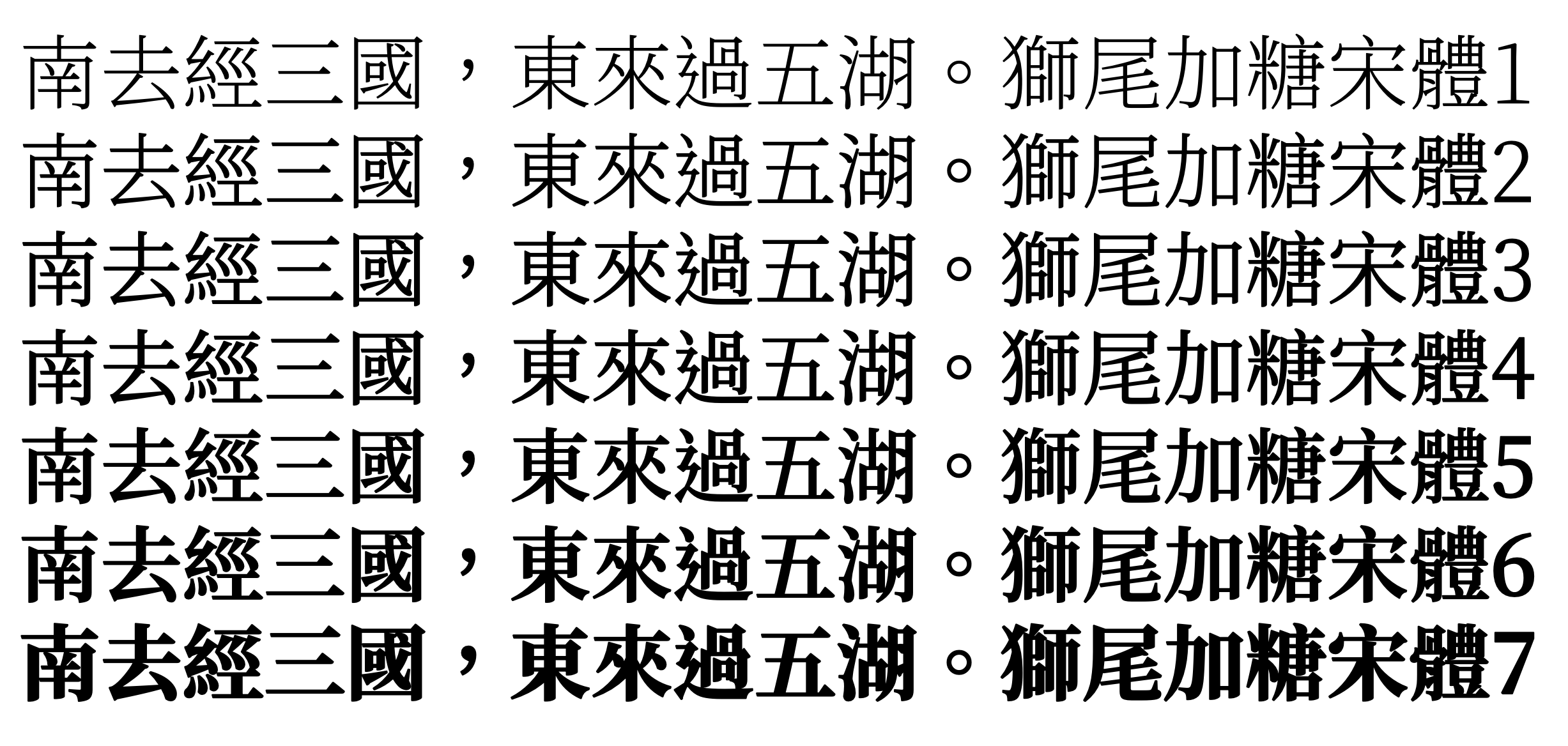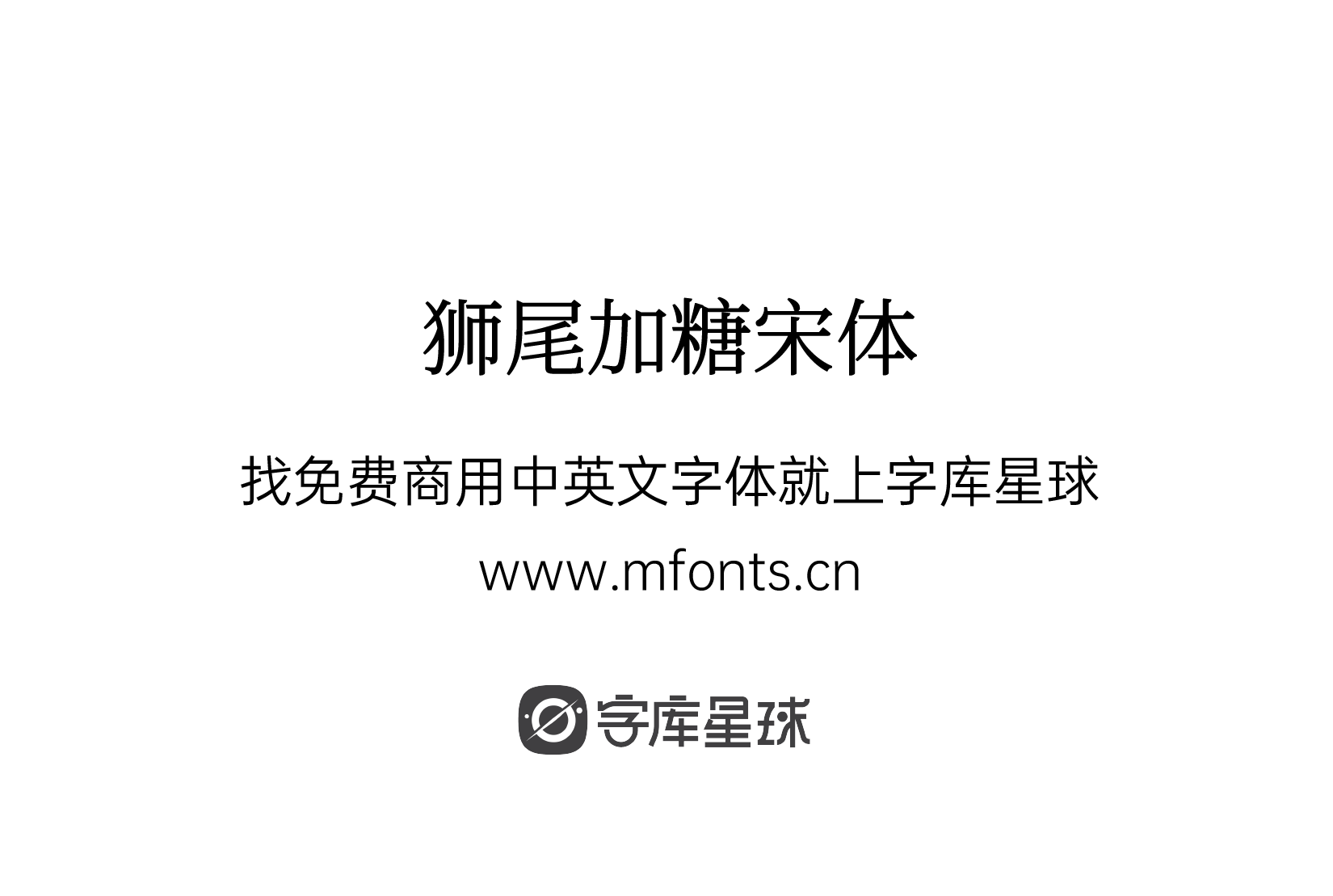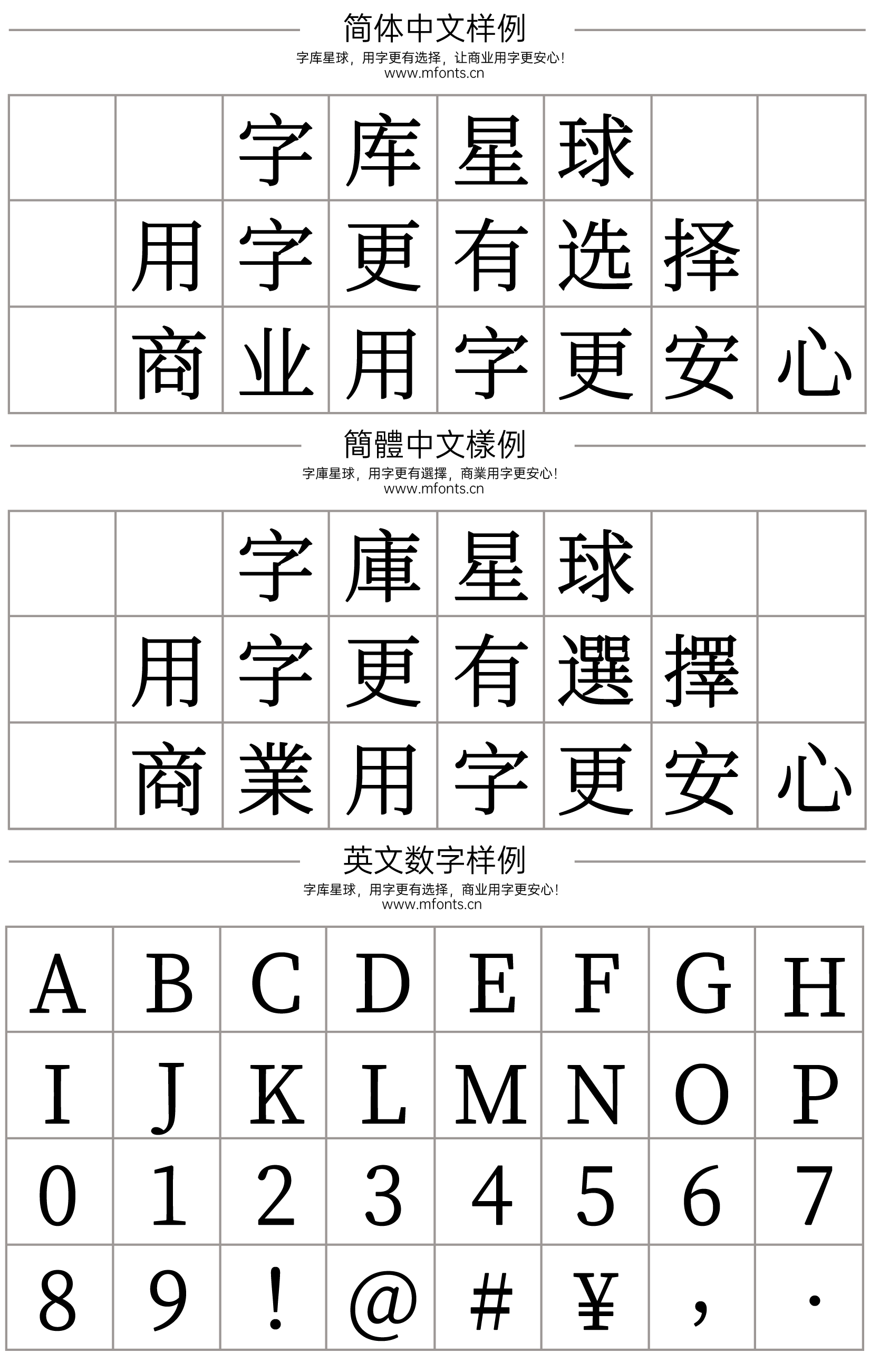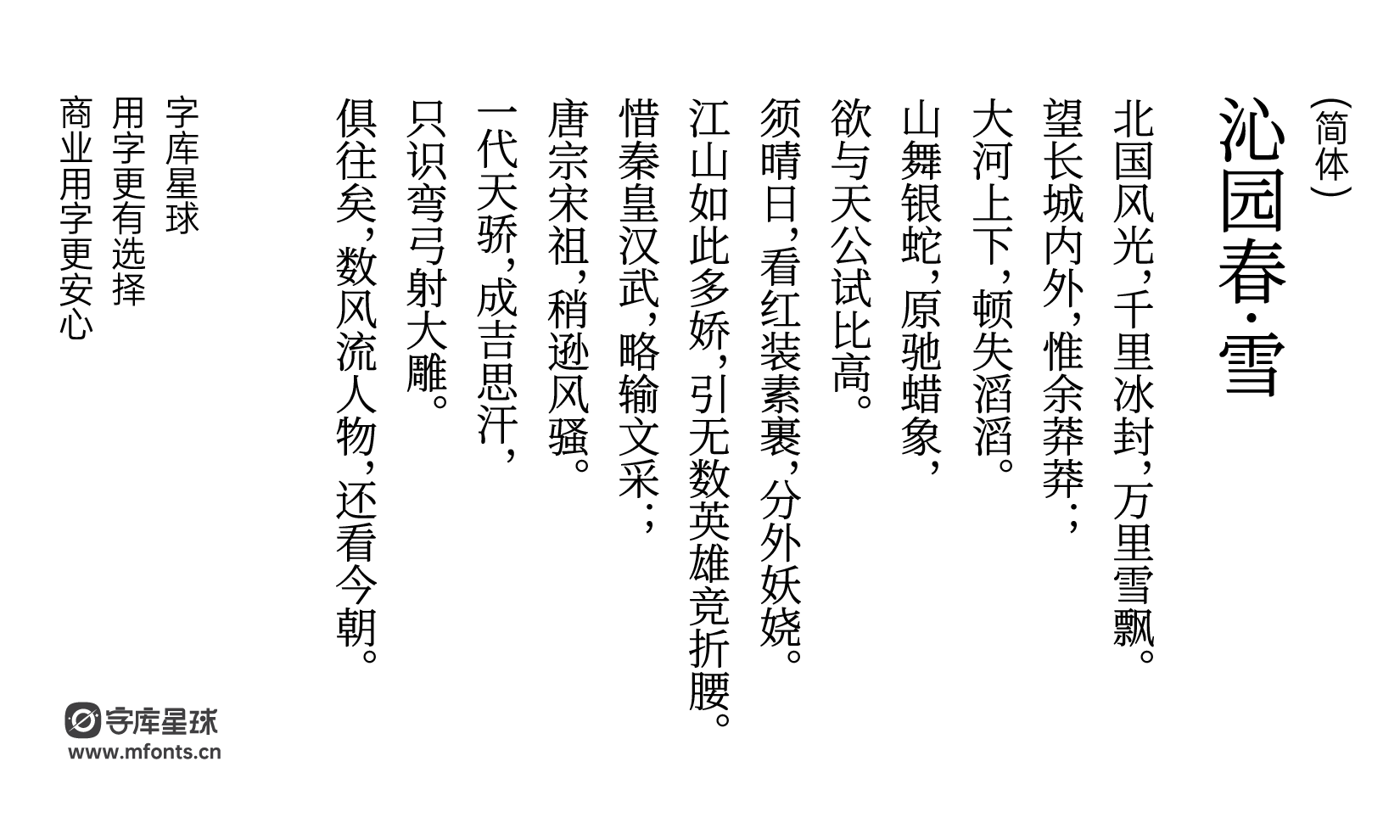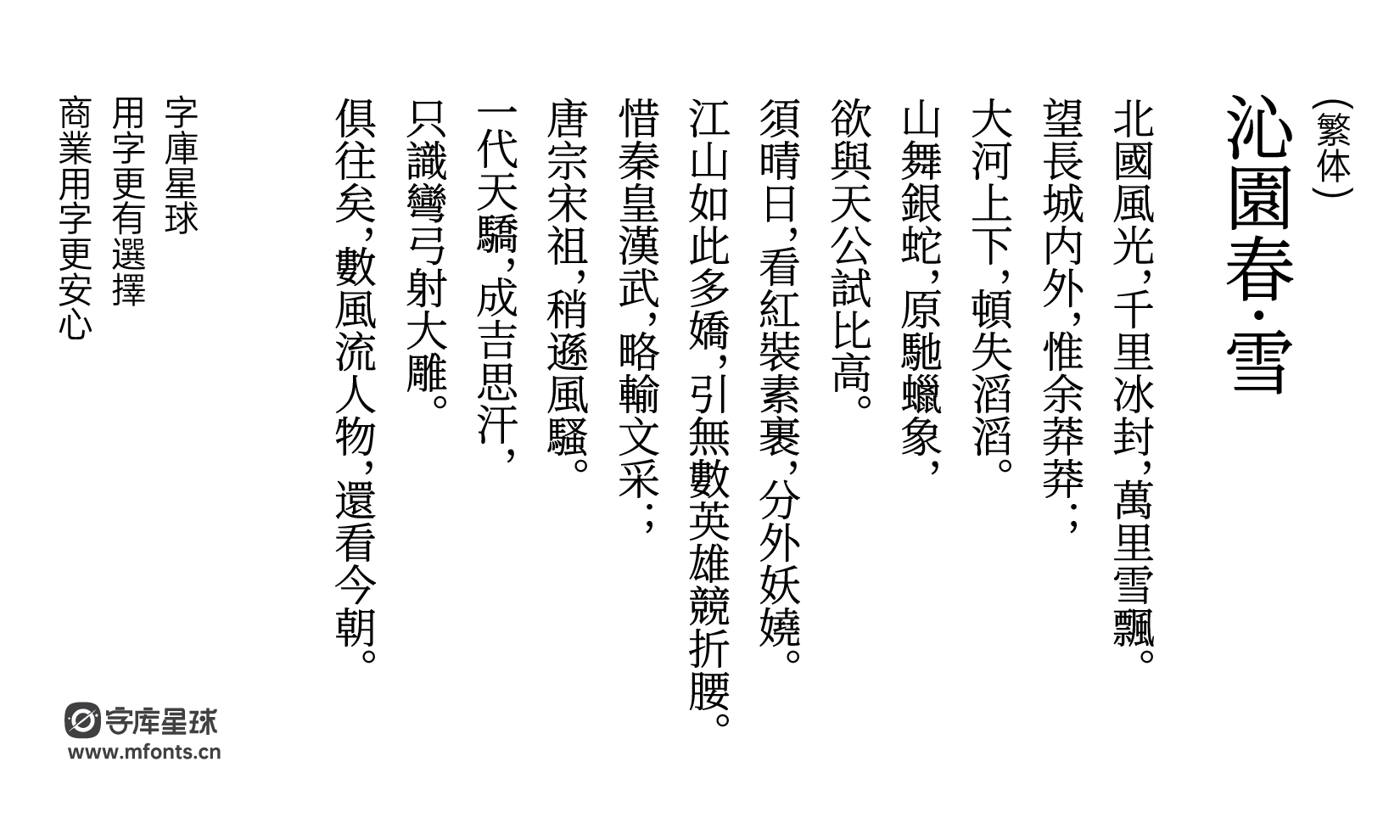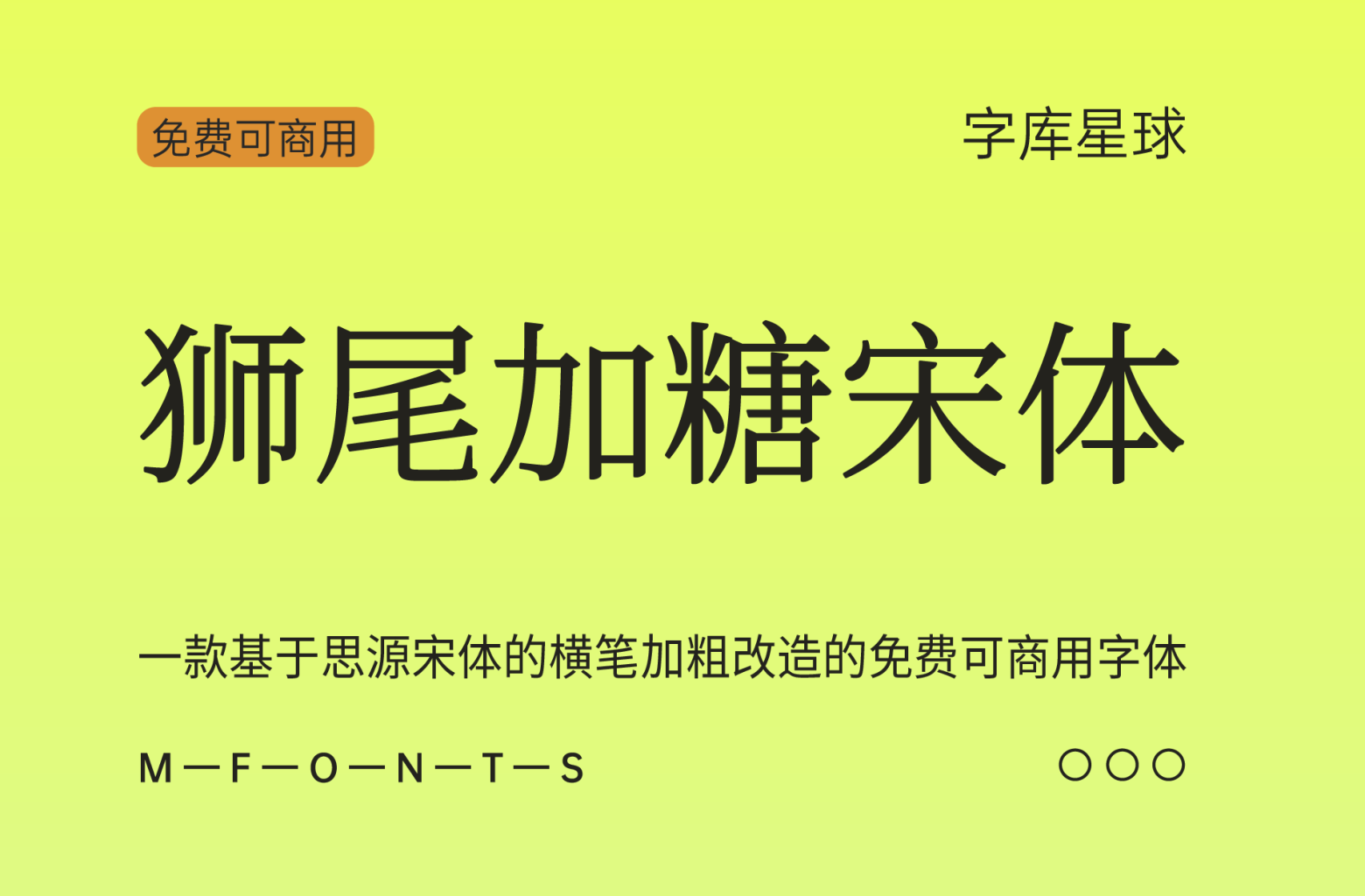
狮尾加糖宋体
狮尾加糖宋体是一款基于思源宋体的横笔加粗改造的免费可商用字体。支持简体中文、繁体中文、韩文与日文。
狮尾加糖宋体设计上针对笔画粗细支援7种字重,所以不论大标、小标、简单的段落排版都能清晰辨识:
与思源宋体比较第一行是狮尾加糖宋体,第二行是原版的思源宋体:
• 在「肉」、「糸」、「女」、「辶」、「食」的笔画,狮尾比较相似台湾教育部推荐字体笔顺,适合教育用途。
• 在「草」部的笔画,狮尾是分开的二个部份。
• 字体里的「草字头部首」中间该不该连起来,「肉字旁部首」该不该变成「月」,要不要把手写习惯代入印刷字体?整体看来,会不会影响视觉的延伸性?会不会影响印刷的可行性与阅读的便利性?
字体后面的 SC,JP,TC是什意思?
• SC是 Simplified Chinese 简体中文,代表大陆习惯字形。
• TC是 Traditional Chinese 繁体中文,代表港台习惯的字形。
• JP是 Japanese 日文,代表日本习惯字形。
• 相同一个字,在不地区的书写方式可能会略有不同。